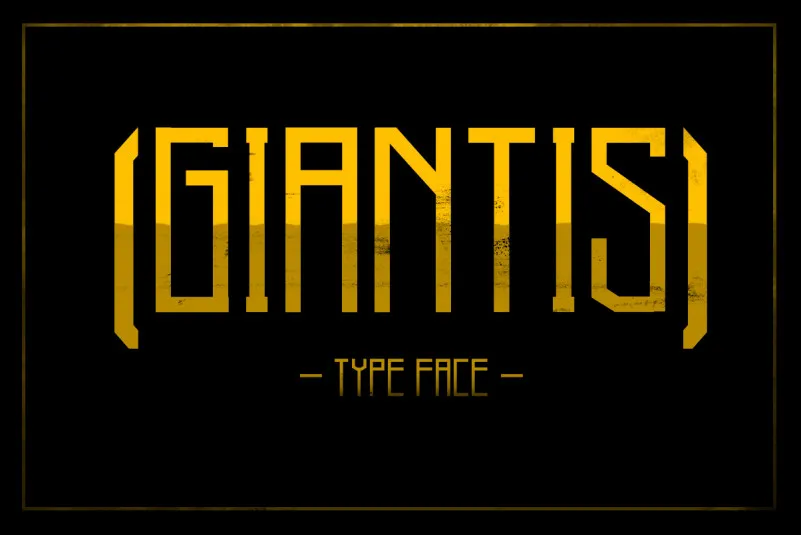
Giantis Typeface – Download Grátis
Giantis é uma tipografia em letra gótica sem serif que surge da inspiração num simples retângulo geométrico. Esta elegante fonte do tipo retro foi criada pelo designer hamlanatype e traz um toque minimalista e limpo à sua utilização. Suas linhas retas e puras remetem a uma arquitetura de linhas rectilineares, ideal para textos em espaços grandiosos e arquitetônicos. Uma versão do tipo antigo da Giantis é perfeita para projetos que buscam um estilo clássico, sem deixar de lado o conforto e a facilidade na digitação. Tornando-se uma fonte perfeita para criações que exijam modernidade e elegância ao mesmo tempo.